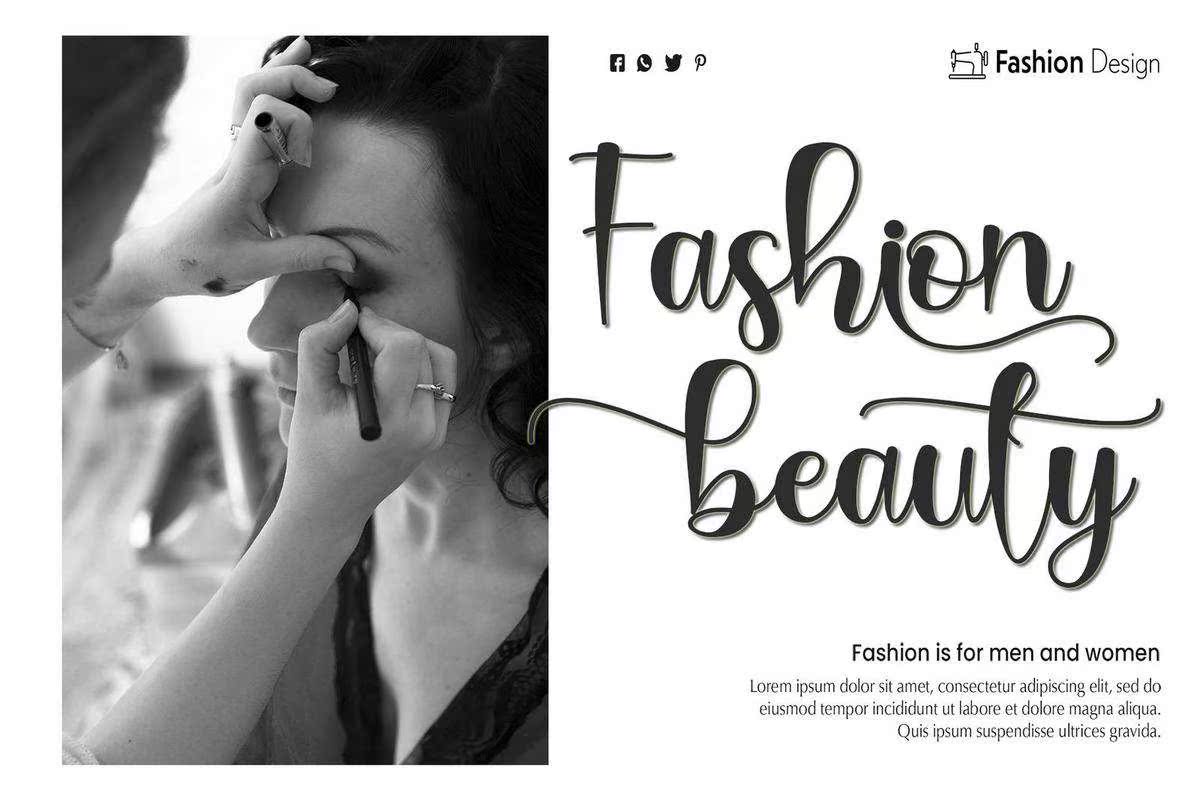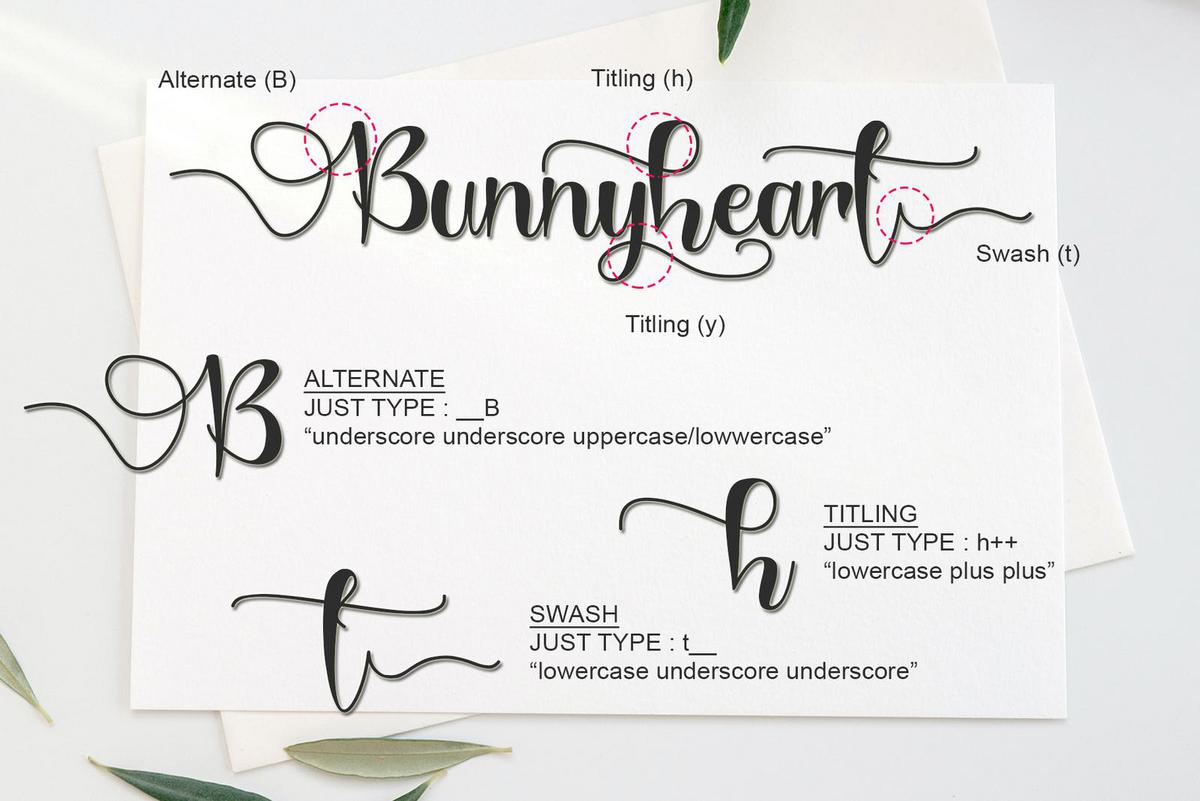
BunnyHeartFonts是一款现代化的AlligraphyFontBylettRafaStudio。它具有流动的字母,可以让您的设计与CuteModel保持一致。BunnyHeartFonts是完美的;徽标、问候卡、包装设计、耐磨性、工艺设计、任何项目、书名、婚礼宣传、包装等。BunnyHeartFonts是一款现代化的AlligraphyFontBylettRafaStudio。它的流动字母将使您的设计与CuteModel相一致。BunnyHeartFonts完美;徽标、问候卡、包装设计、耐磨性、工艺设计、任何项目、书名、婚礼宣传、包装等。